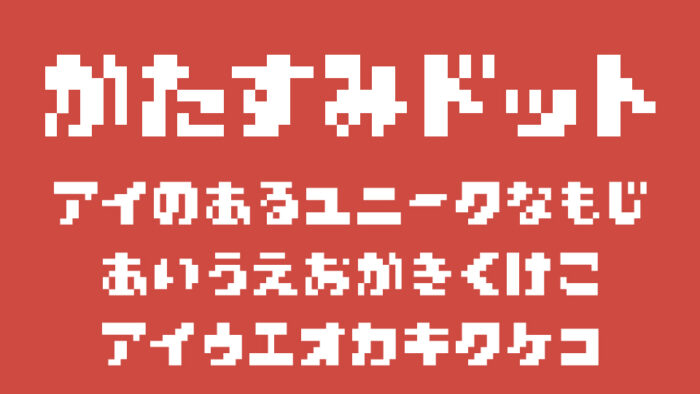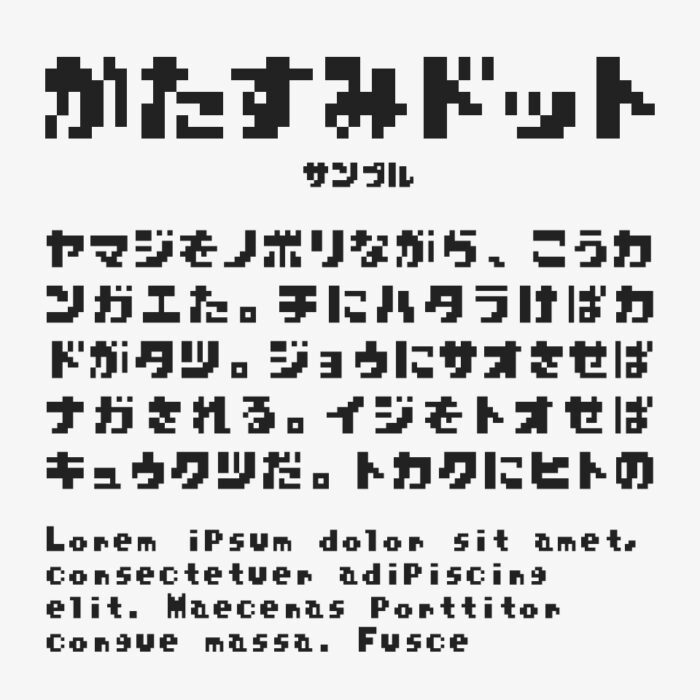
かたすみドット
かたすみドットフォントは、8×8のドット絵で構成された、太めで個性が際立つ可愛らしいドットフォントです。
文字の四隅がくっきりと角ばったデザインになっており、どこかゲームボーイ時代の画面を思い出させるような、懐かしさとレトロ感が感じられます。
なお、サイズを8の倍数で使用すると、ドットの輪郭がにじまず、よりきれいな状態で表示できるとのこと。ドットのシャープさを活かしたい場合は、サイズ設定を意識して使うのがおすすめです。
細めに作られた「かたすみドット ほそじx8y8」というバリエーションも用意されています。